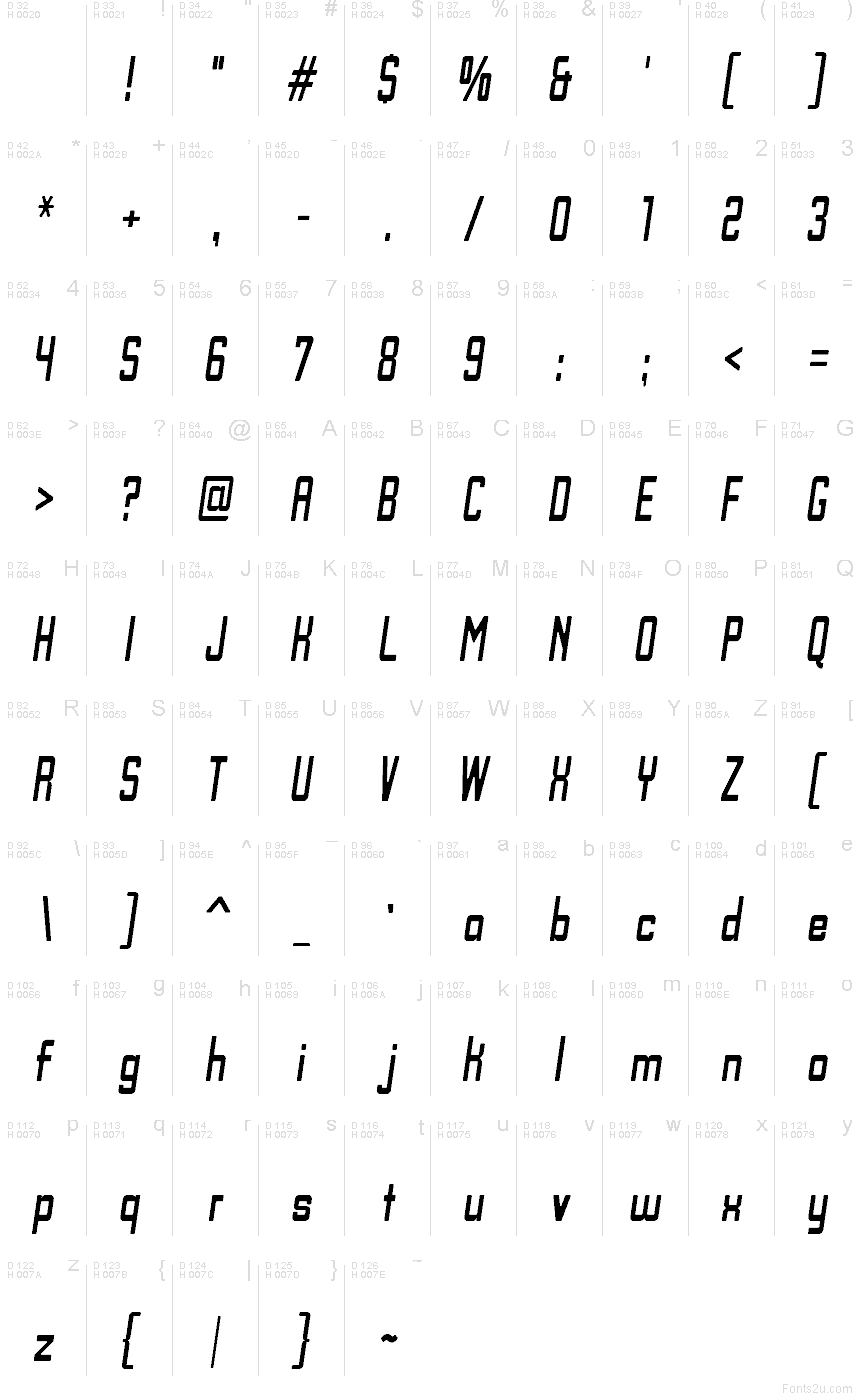
Nova Bomb Condensed Oblique od Tension Type je bezplatné zúžené techno display písmo so strmým sklonom dopredu, tupými spojmi a veľmi tesne usporiadanými proporciami. Jeho vysoké písmená pôsobia rýchlo a mechanicky.
Motorsport, arkádové preteky a futuristická doprava sú pre toto komprimované písmo prirodzenými témami. Uhlové tvary sa hodia na branding tímov, hernú grafiku a plagáty podujatí, kde vyjadrujú rýchlosť bez toho, aby sa spoliehali na pridané efekty. Na merchandise sa nápisy môžu stať súčasťou pretekárskeho pruhu alebo emblému inšpirovaného strojmi namiesto toho, aby slúžili ako bežný text.
Toto písmo vychádza zo skice vytvorenej pred niekoľkými rokmi. Pôvodne malo byť ručne kresleným písmom, ale vývoj nepokračoval. V roku 2026 som sa rozhodol sa k nemu vrátiť. Nie je určené na súvislý text.
This type design was based on a sketch I did a bunch of years ago. It was initially intended as a hand drawn typeface. I started it, but I never really made any progress. In 2026 I decided to give it another shot. Its a bit sci fi, a lot square. Good for large text and logos etc. Not intended for body copy at all.